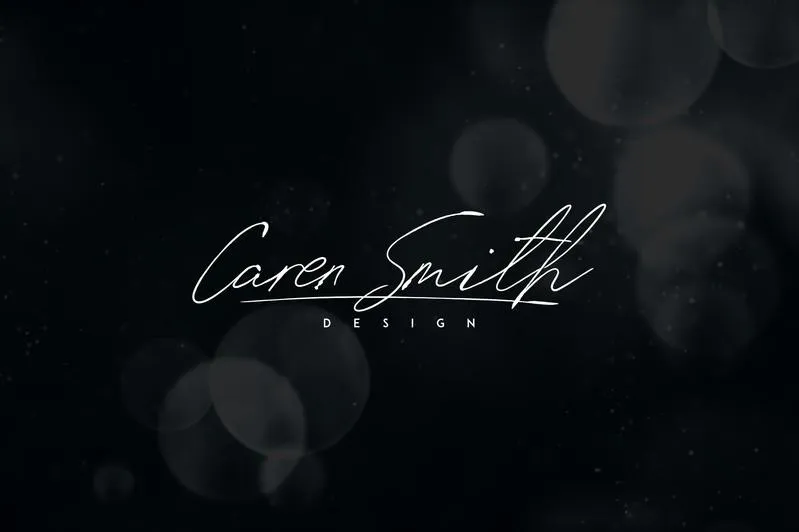
Signature Vp – Handwritten Font – Download Grátis
Signature Vp – Handwritten Font é uma escolha perfeita para projetos de marcação, designs de móveis de casa, embalagens de produtos e cabeçalhos de revistas. Seu estilo elegante e autêntico permite que sua assinatura ou texto seja o centro das atenções, sejam eles em um fundo gráfico inspirador ou numa imagem de produto. Além disso, ela adiciona um toque sofisticado a qualquer projeto, tornando-a uma excelente opção para overlay textual sobre imagens de fundo, oferecendo aos designers flexibilidade e criatividade sem limites. Seja você que seja designer gráfico profissional ou iniciante, esta fonte escrita a mão é definitivamente um recurso indispensável.